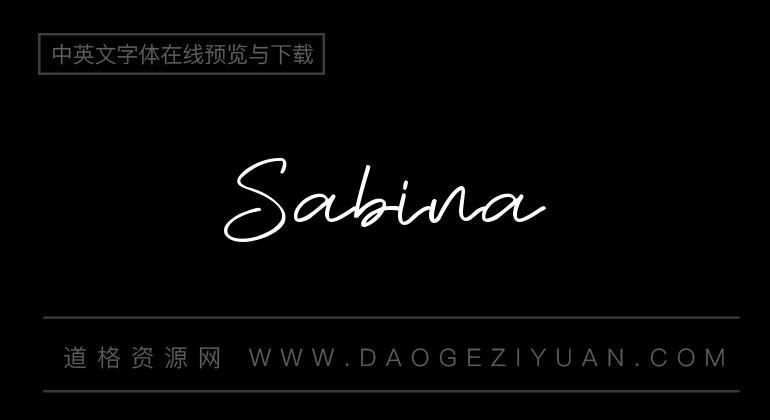
Sabina 字体是一款由西班牙设计师 Sabina Chipară 创作的新字体。它采用了欧洲传统的线条风格,融合了现代多样性,是一款拥有多种字体形式的综合性字体。Sabina 字体具有流畅的线条,精美的视觉效果,适合用于报纸、杂志、书籍、海报、网站等各种印刷和设计项目。内容介绍
Sabina是一款非常不错的手写艺术字体,具有很好的视觉感,适合于文化类的宣传设计、商业类品牌的广告和产品包装设计以及个性化文字排版等较多场景。